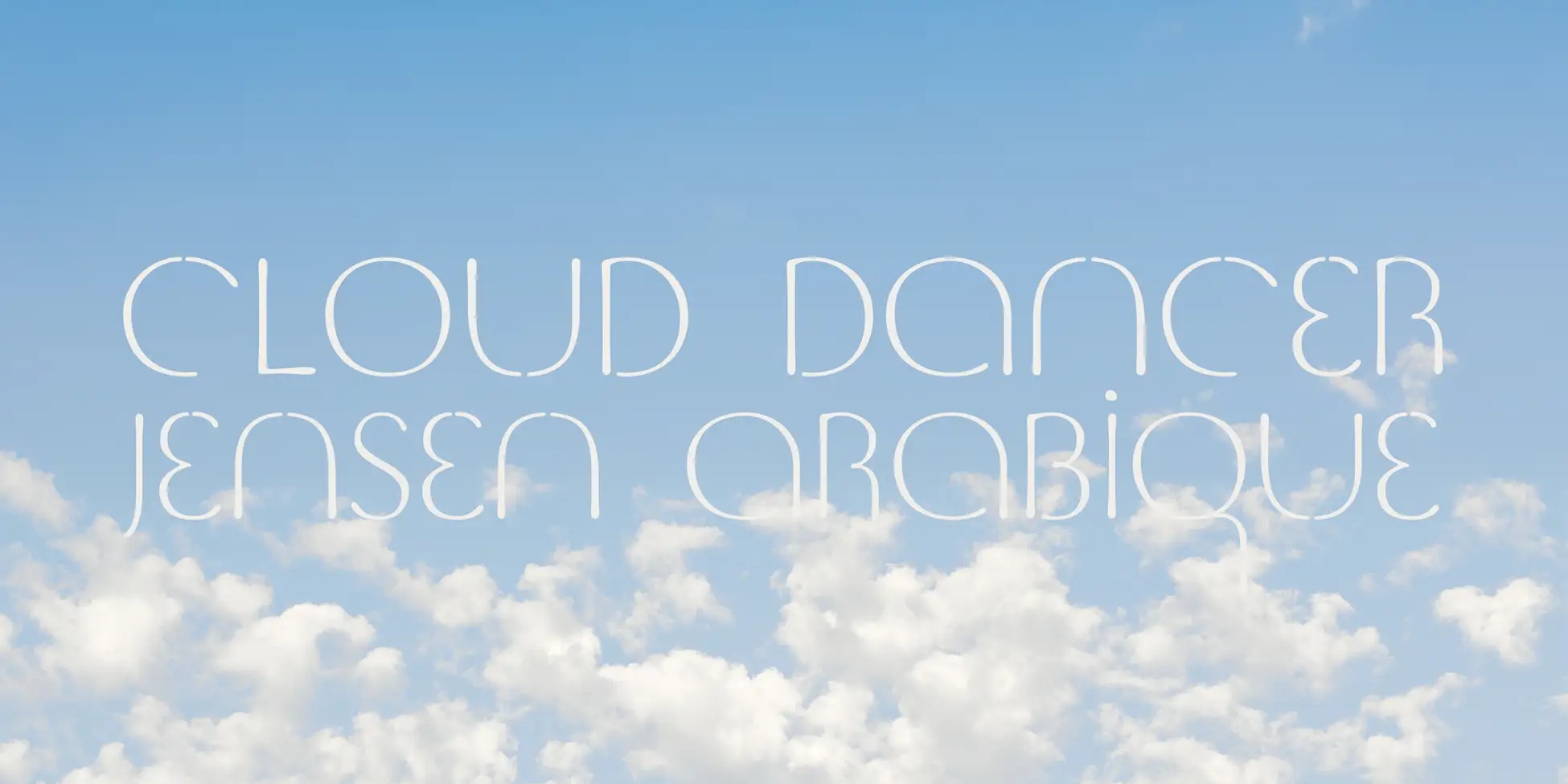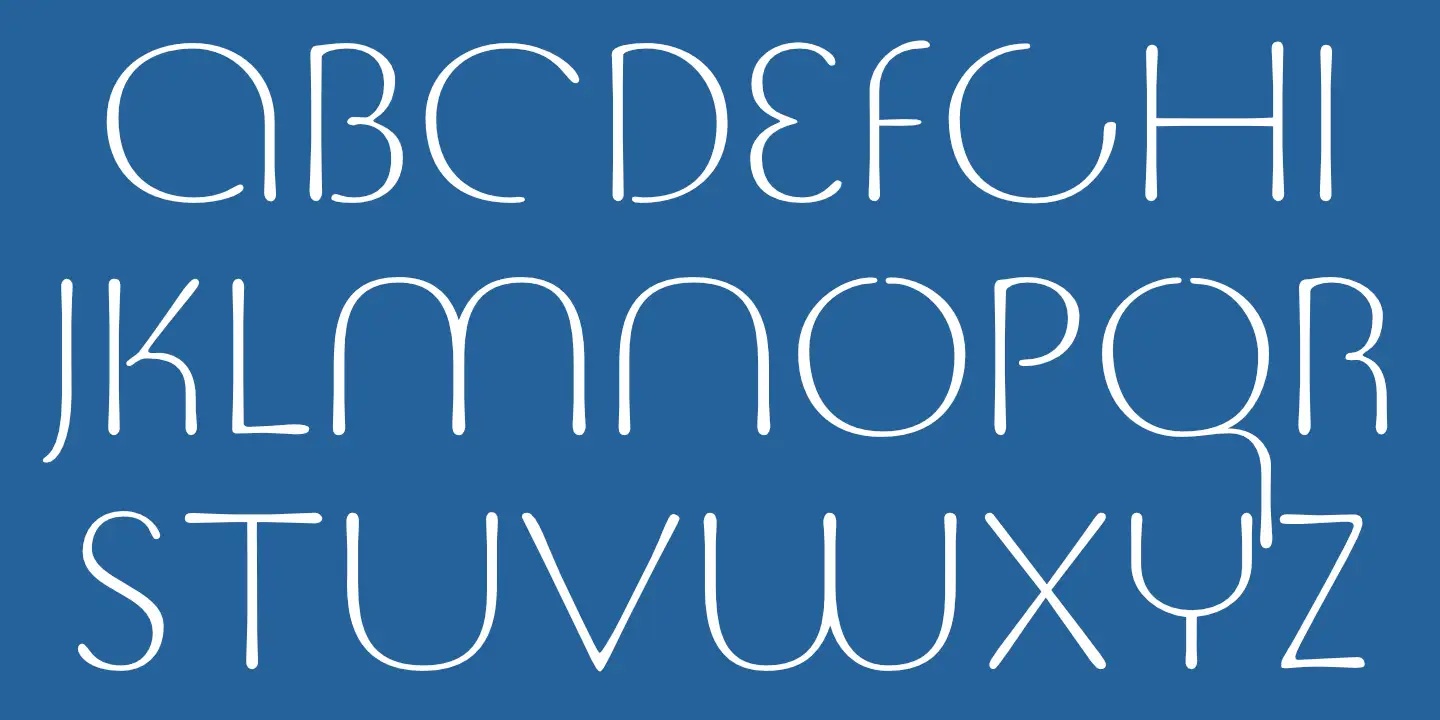
Monotype、2026年のPantoneカラー・オブ・ザ・イヤーにタイポグラフィー表現を提供
書体デザインとテクノロジーのグローバルリーダーであるMonotype Imaging Inc.(本社:米国マサチューセッツ州ウーバン、CEO:ナイナン・チャッコ(Ninan Chacko)、以下Monotype)は、2026年のPantoneカラー・オブ・ザ・イヤー「PANTONE 11-4201 Cloud Dancer」に合わせた初のタイポグラフィー表現として書体「Jensen Arabique™」を選定いたしました。
書体「Jensen Arabique」と選定背景について
本書体の選定は、Monotype® シニア・エグゼクティブ・クリエイティブ・タイプ・ディレクターである Charles Nixが行いました。「Jensen Arabique」は、独立系タイプデザイナーであるJason Castleが1990年代にデザインとデジタル化を行った書体で、デザイナーのGustav Jensenが1933年に制作した稀少なアルファベットサンプルブックに基づいています。
Charles Nixは、タイポグラフィーの経験、文化的な参照点、手書きの文字のスケッチ、そしてMonotypeの検索・発見ツール(WhatTheFontおよび新たに登場したMonotype AI検索ツールなど)も使いながら候補を絞り込み、最終的に「Jensen Arabique」を選びました。
「PANTONE 11-4201 Cloud Dancer」は、シンプルさや休息への願望を象徴する色であり、その穏やかな特徴は「Jensen Arabique」の上品で読みやすいフォルムと理想的に調和します。手作りのような質感を持つこの書体は、静けさや落ち着きを表現しつつ、現代的なデザインの美しさを引き立てます。
書体と色の組み合わせ
書体と色の組み合わせは、デザインにおいて欠かせない要素であり、すべてのデザイナーがクリエイティブな決定をする際の中心的な役割を果たします。Monotypeの「2025 Fonts, Feels, & Reels」調査では、Z世代の79%、ミレニアル世代の78%が、SNSで魅力的な投稿を作るためにフォント選びが重要だと感じていることがわかりました。12月4日にニューヨークで開催された、2026年の「Pantoneカラー・オブ・ザ・イヤー」の発表イベントの会場では、書体「Jensen Arabique」を使ったネオンアートが展示され、色と文字の組み合わせによってダイナミックで没入感のある体験が表現されました。
このタイポグラフィ表現は、色と文字が持つ深い関係を際立たせ、Charles Nixが「創造的な共感覚」と呼ぶ、新しい感覚を生み出します。MonotypeとPantoneのパートナーシップは、感情や個性、文化的意義を高めるデザインの可能性を示すものです。また、この取り組みは、クリエイティブなプロフェッショナルたちが求める、高品質かつAIを活用したフォント選択ツールのニーズにも応えるものであり、デザインにおける発見や実験、視覚的な統一性をサポートします。
クリエイターたちからのコメント
「Jensen Arabiqueが、今の時代に見事に響いていることを知り、とても感慨深いです」とCastleTypeの創設者、Jason Castleは述べています。「このフォントを初めて制作した時、その形が優美で心を穏やかにするものだと感じました。フォントデザインの特性として、いつ、どこでそのデザインが共鳴するかを予測するのは難しいものですが、このフォントが現代の文脈の中で新しい意味を見出している様子を見ることができ、とても興奮しています。」
「共感覚とは、一つの感覚が別の感覚を引き起こすことです。デザイナーやクリエイティブな人々は、『文化的共感覚者』と言えます。彼らは直感や経験、そしてツールを活用しながら、毎日色と文字を組み合わせて感情や意味を表現しています」とCharles Nixは語ります。
「今年は初めて、『Pantoneカラー・オブ・ザ・イヤー』にインスパイアされたタイポグラフィ表現を提案し、Jensen Arabiqueを今年の選定色であるPANTONE 11-4201 Cloud Dancerと組み合わせました。デザインとは、慎重なキュレーションのプロセスです。色は文字を必要とし、文字は色を必要とします。豊富なクリエイティブ要素が溢れる中で理想的な組み合わせを見つけることは、絶えず進化し続けるアートです。そしてそのプロセスは、AIを含む革新的な検索ツールや発見ツールによってさらに進化しています。」